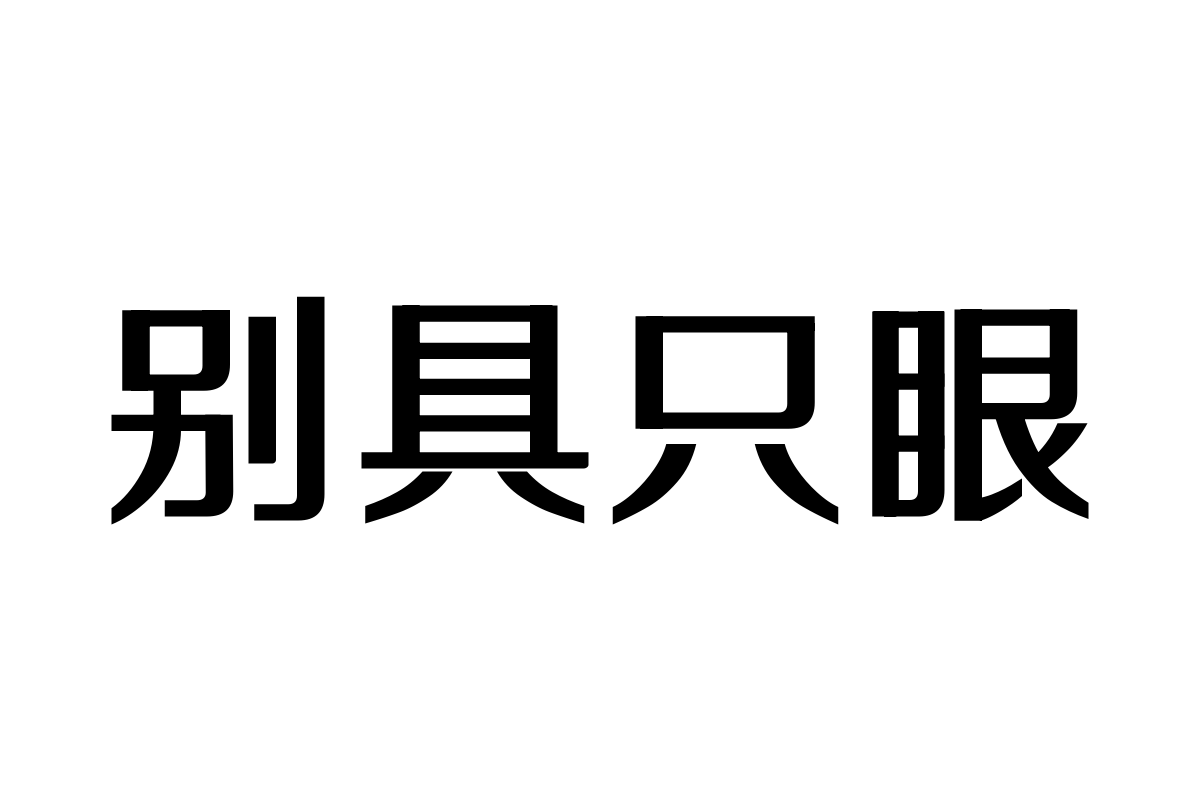
三极正典黑字体是一种具有现代感和科技感的无衬线字体,它以其简洁、清晰的设计而受到广泛欢迎。这种字体的特点是没有衬线(即没有像传统衬线字体那样的小竖杠),这使得它在视觉上更加现代和易于阅读。
三极正典黑字体适用于各种类型的文本,包括标题、正文、广告牌等。它的可读性非常好,即使在较大的尺寸下也能保持清晰。此外,这种字体还具有很好的适应性,可以用于各种背景颜色和图像,使得它在网页设计和品牌标识中非常实用。